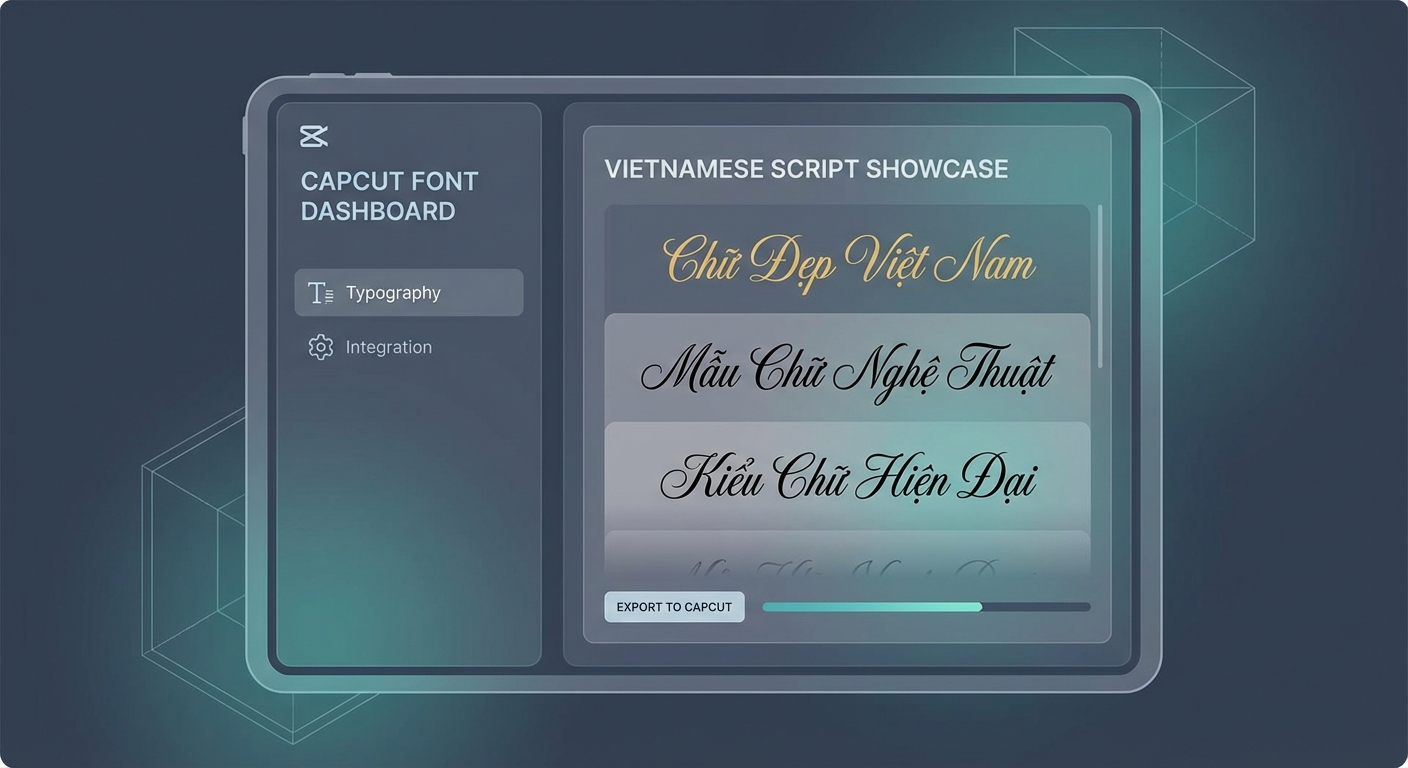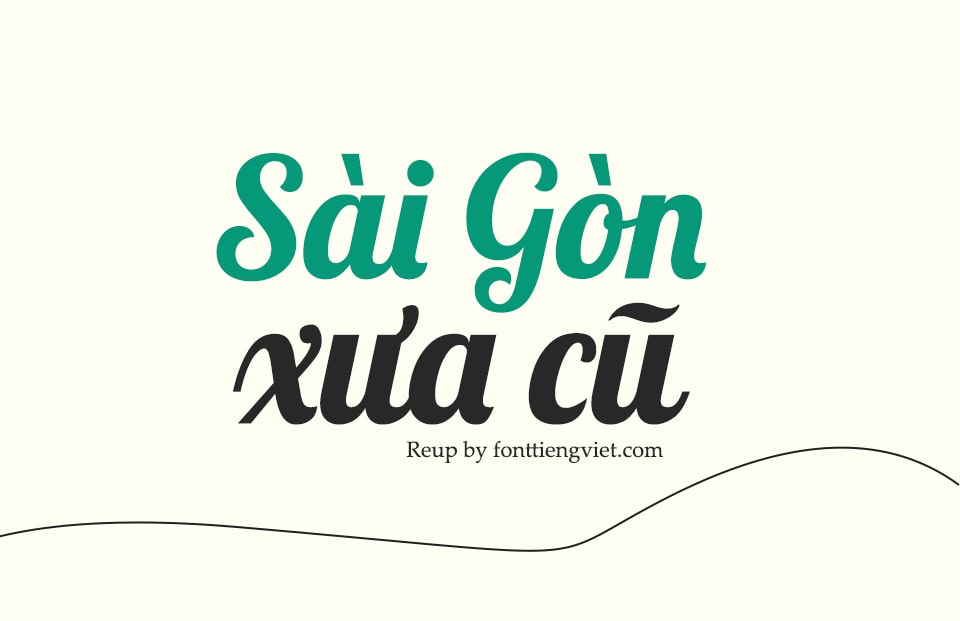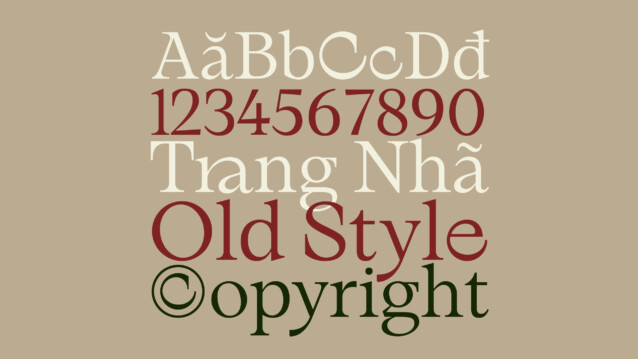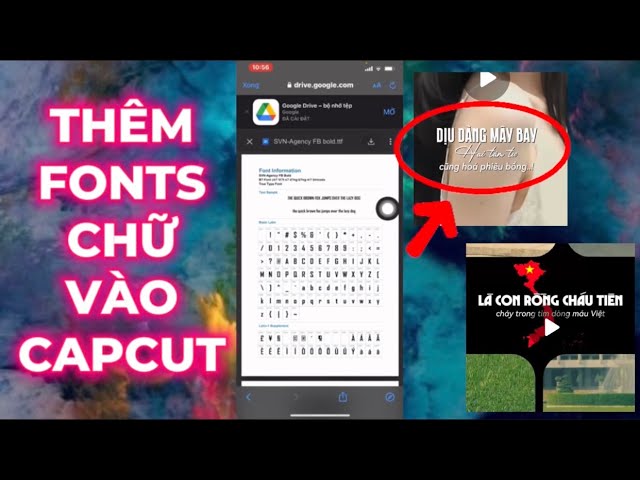
Việc lựa chọn font chữ CapCut tiếng Việt đẹp giúp video của bạn trở nên chuyên nghiệp và thu hút hơn. Bài viết này sẽ cung cấp danh sách phông chữ xu hướng và hướng dẫn chi tiết cách cài đặt nhanh chóng.
Trong kỷ nguyên video ngắn lên ngôi, việc chỉnh sửa video không chỉ dừng lại ở cắt ghép hình ảnh. Việc sử dụng font chữ CapCut tiếng Việt đẹp đang trở thành yếu tố quyết định sự thành công của một video.Một phông chữ thẩm mỹ kết hợp với hiệu ứng làm chữ chạy trên capcut sẽ giúp truyền tải thông điệp rõ ràng.. Nó cũng tạo ra dấu ấn cá nhân mạnh mẽ cho người sáng tạo nội dung.
Tại sao font chữ CapCut tiếng Việt đẹp lại quan trọng cho video?
Font chữ CapCut tiếng Việt đẹp đóng vai trò quyết định trong việc truyền tải thông điệp và giữ chân người xem. Một phông chữ thẩm mỹ, dễ đọc không chỉ giúp video trông chuyên nghiệp hơn. Nó còn thể hiện rõ phong cách cá nhân của người sáng tạo nội dung trên mạng xã hội.
Dưới đây là những lý do chính khiến typography (nghệ thuật chữ) trở nên quan trọng:
- Thu hút sự chú ý: Trong 3 giây đầu tiên, một tiêu đề nổi bật sẽ giữ người xem ở lại.
- Định hình phong cách: Font chữ mềm mại phù hợp với video vlog nhẹ nhàng. Font chữ đậm, góc cạnh lại phù hợp với video công nghệ hoặc thể thao.
- Tăng tính chuyên nghiệp: Sử dụng font chữ không bị lỗi dấu thể hiện sự chỉn chu của người làm video.
Những font chữ CapCut tiếng Việt đẹp nào đang là xu hướng năm 2026?
Những font chữ CapCut tiếng Việt đẹp đang là xu hướng năm 2026 bao gồm các dòng font viết tay mềm mại, font Sans-serif hiện đại và font Retro cổ điển. Các phông chữ tiêu biểu như Meimei Fluffy, Be Vietnam Pro và Montserrat đang được sử dụng rộng rãi trên các nền tảng video ngắn.